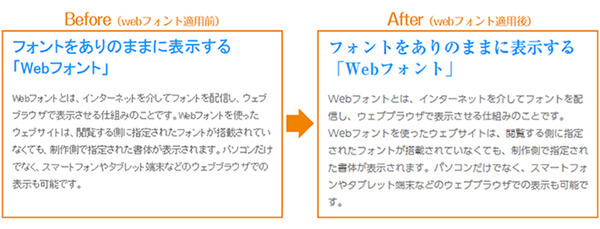
さくらサーバ利用者はモリサワのWebフォント30種を「無料」で利用可能に!
どんな閲覧環境でもデザイナーが指定したフォントタイプ通りに表示してくれるWebフォントの活用は今後も進んでいきそうです。
キャンペーンサイトなどでちょっと特徴のあるWebフォントがサイト全体に使われているのを見かけますが、閲覧者目線ではインパクトが強く残りますよね。また開発者目線でも、それまで画像で見出しを作ると修正が入った時にちょっと大変でしたが、Webフォントなら即座に修正できます。
そんなWebフォントですが、レンタルサーバでお馴染みの「さくらインターネット株式会社」とフォント開発などを行う「株式会社モリサワ」が協業して、無料でWebフォントが導入できるようになったというニュースがありました。
つまりさくらインターネットの利用者はWordpressを使う場合、無料でモリサワのWebフォント30種を使えるようになるそうです。使えるWebフォントのタイプは下図。
ベーシックな書体から個性的な書体、視認性に優れたユニバーサルデザインを取り入れた書体もそろっており、Webデザインの表現の幅が広がりそうですね!